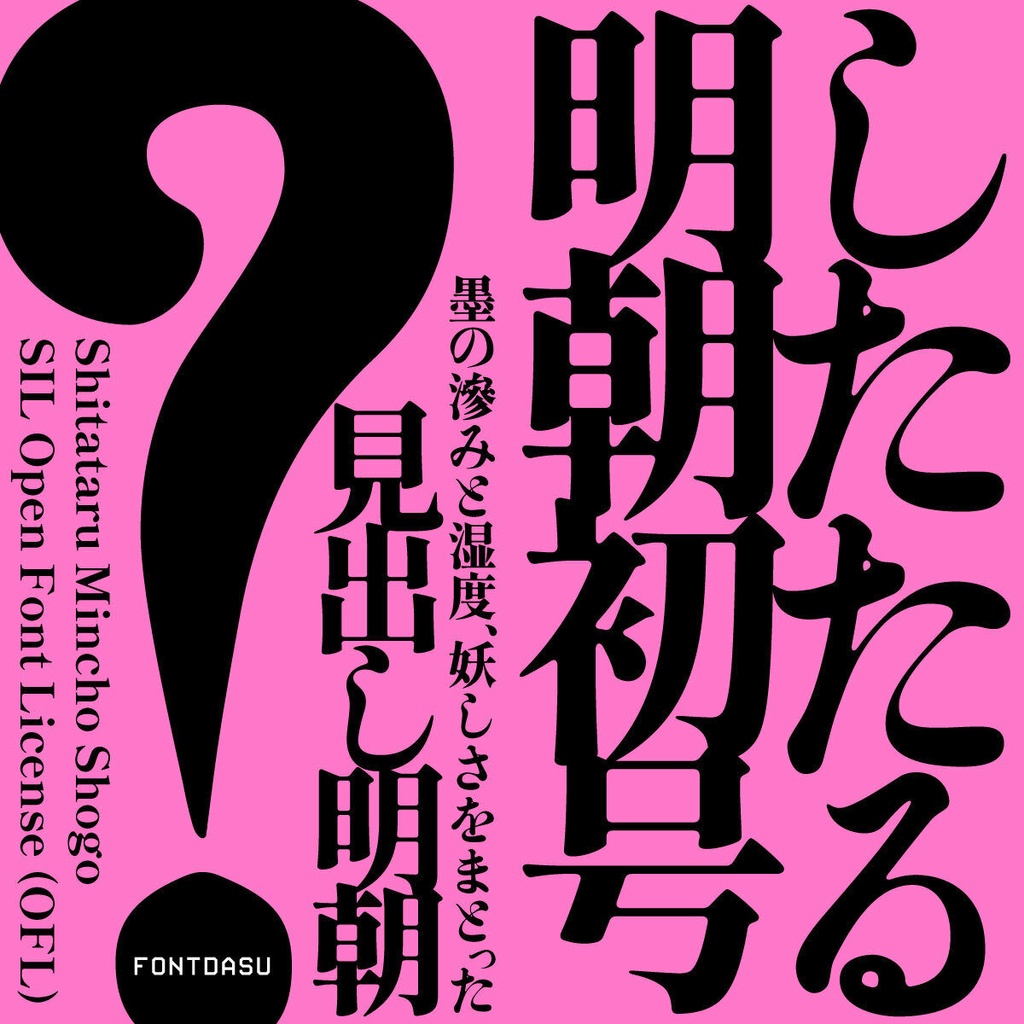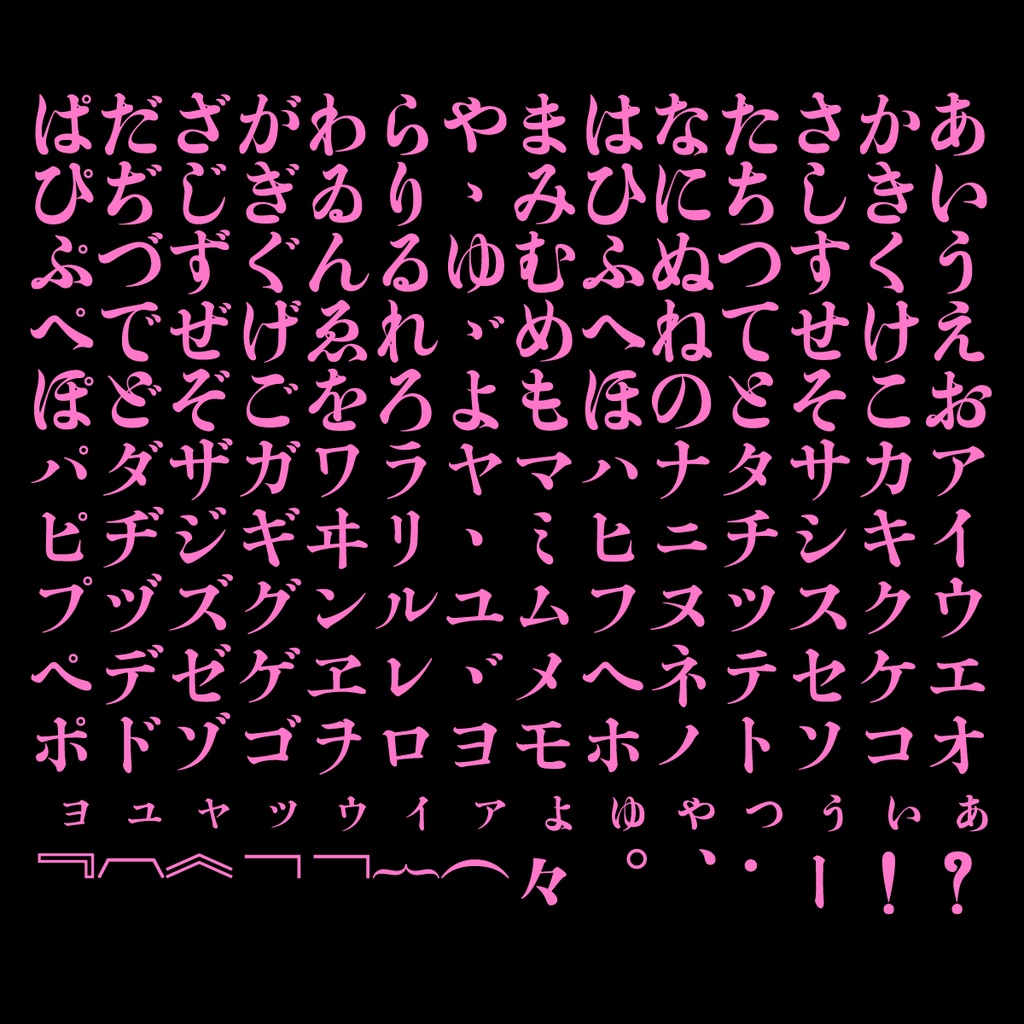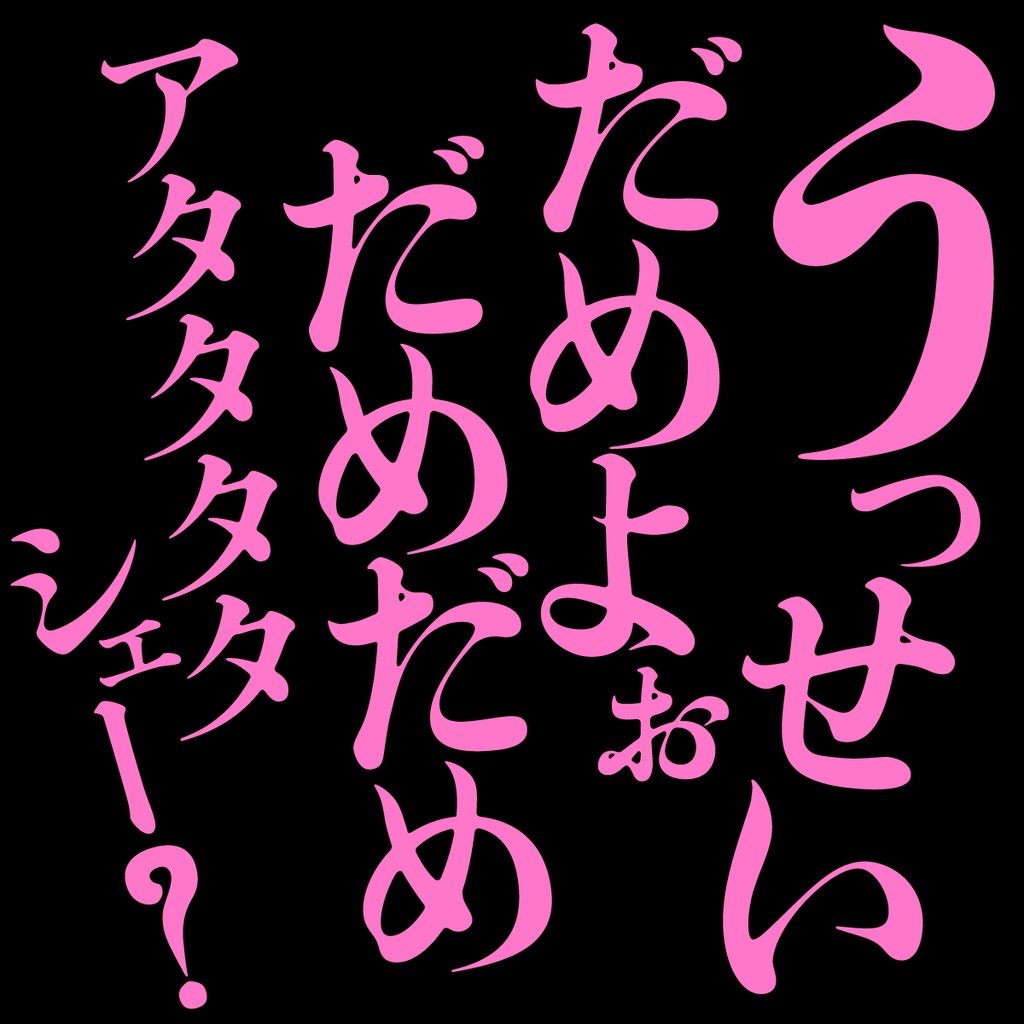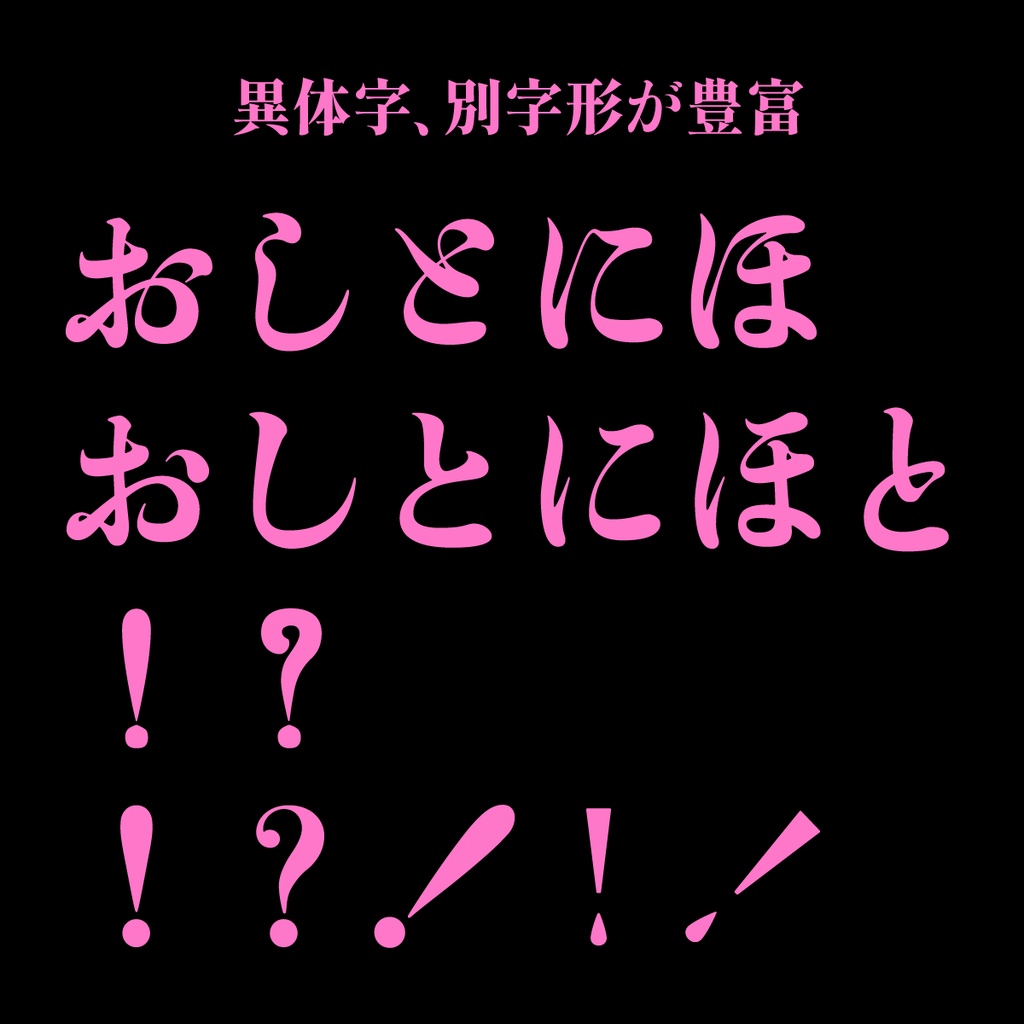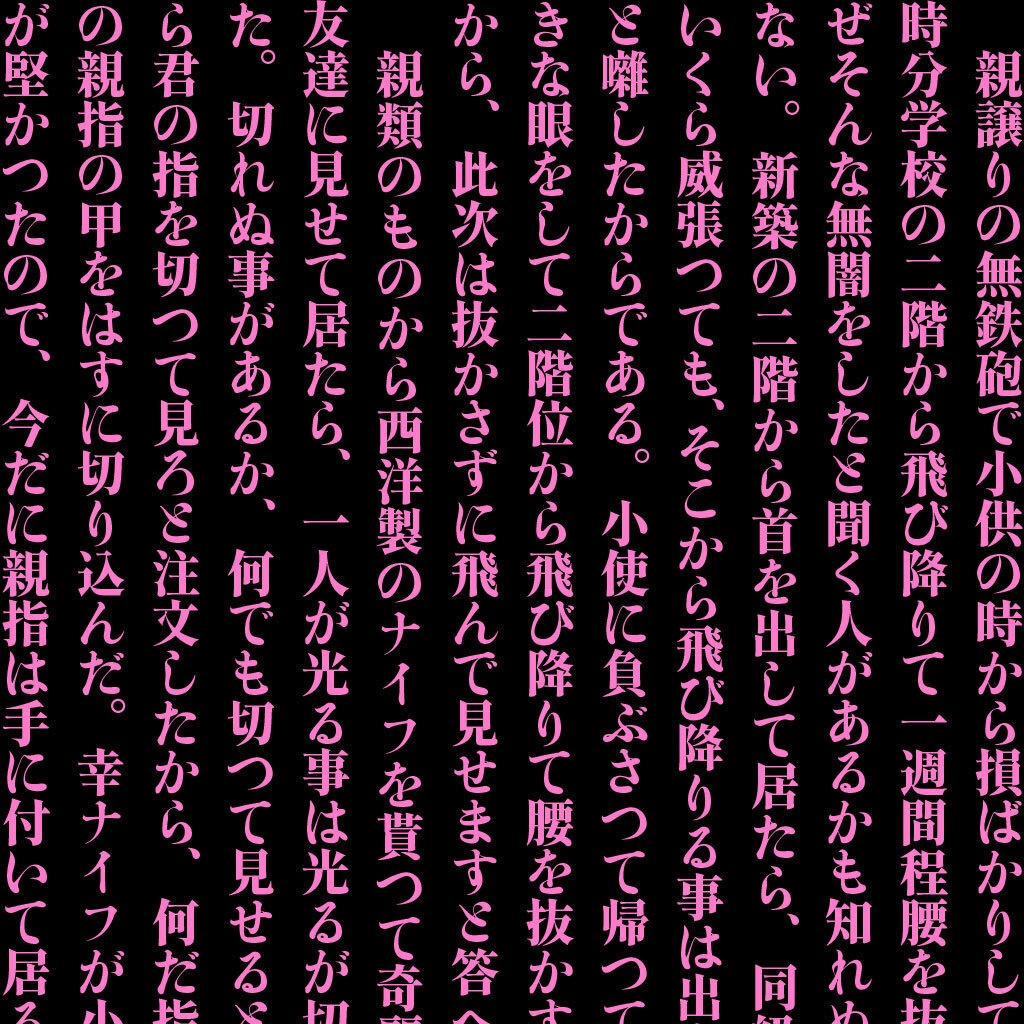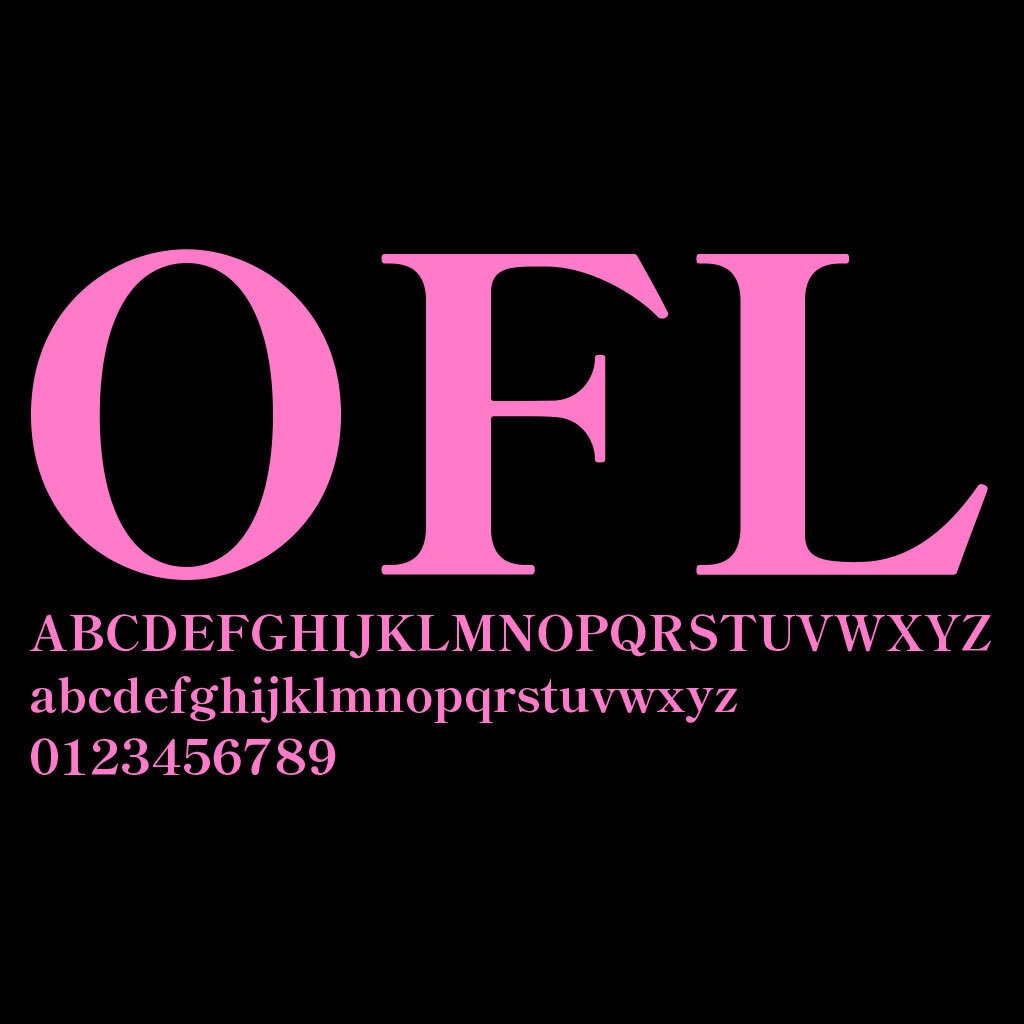
築地初号明朝を下敷きにした見出し用明朝体「したたる明朝初号」(フリーフォント)
「したたる明朝初号」は、墨の湿度と妖しさをまとった、見出し用の日本語明朝体です。 かつて新聞や雑誌の見出しに使われた東京築地活版製造所初号活字とその派生書体を下敷きに、仮名の筆脈をつなげられるだけつなぎ、より“魅せる”書体としてリメイクしました。 ロック、バイオレンス、ホラー、時代劇、エロスまで、端正な明朝では物足りない、強い言葉のための書体です。 漢字は「源流明朝」という「源ノ明朝」派生フォントのものをエッジに丸みを加えて収録し、文字を拡大しても違和感のないようにしています。 「と」や「し」など、一部の文字には古風で癖のある字形を収録しています。 癖が強すぎる場合は、OpenTypeのStylistic Sets機能を使って、標準的な字形へ切り替えられます。 写植で印刷した時代によくあった、画線の交差部分にのボケ足(墨だまりとも言われています)を再現した別ヴァージョン「したたる明朝初号B1」も提供。 濁点喘ぎ(汗喘ぎ/汗濁喘ぎ/濁音喘ぎ)もできる。ハートマークにも濁点がついています。